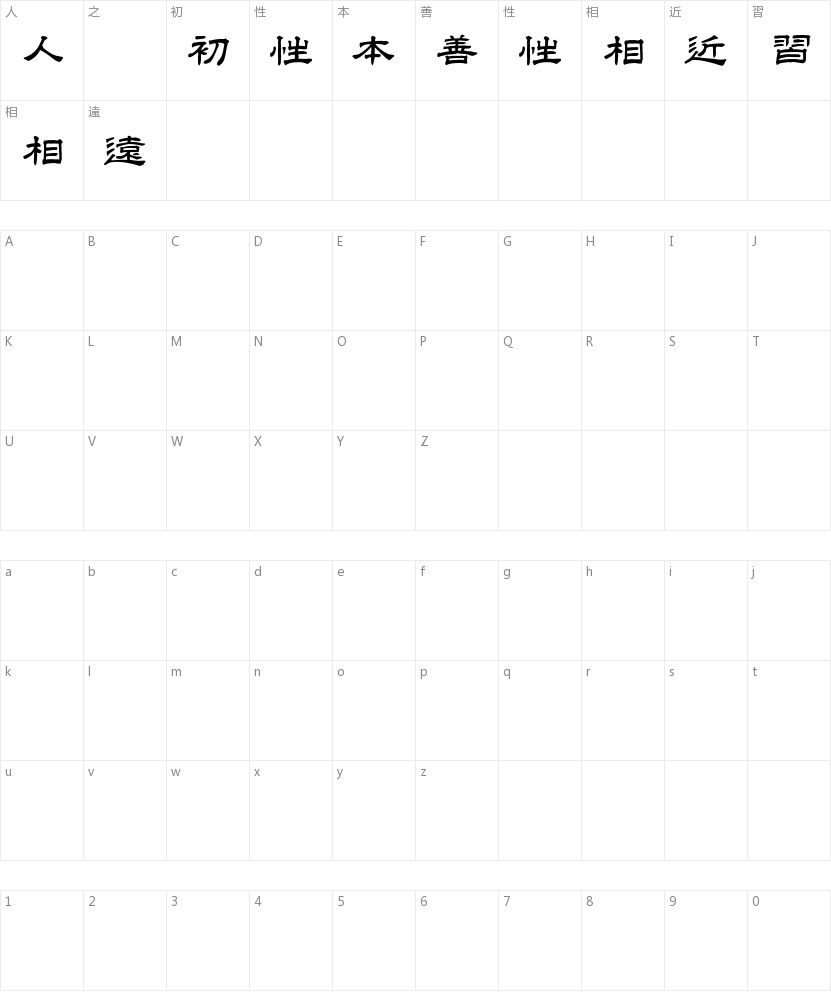
白舟隶书教汉
白舟隶书教汉字体,又称白舟隶书体,是一种中国传统的汉字字体,起源于清代,由著名书法家白舟(1740-1812)创作而成。字体规整,笔画细腻,深受清代书法家、官僚、文人和书法爱好者的喜爱。白舟隶书教汉字体以白舟的书法作品为基础,经过精心制作,形成了一套完整的汉字字体,其特点是笔画细腻,线条优美,笔法简洁,字形统一,十分精美。
白舟隶书教汉是一款非常不错的手写艺术字体,具有很好的视觉感,适合于文化类的宣传设计、商业类品牌的广告和产品包装设计以及个性化文字排版等较多场景。